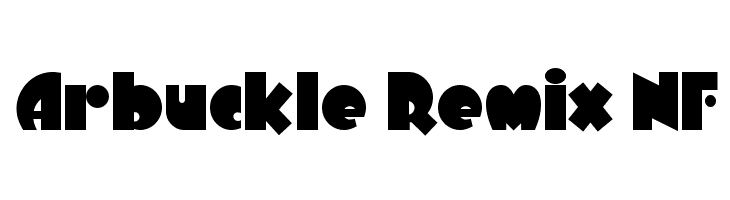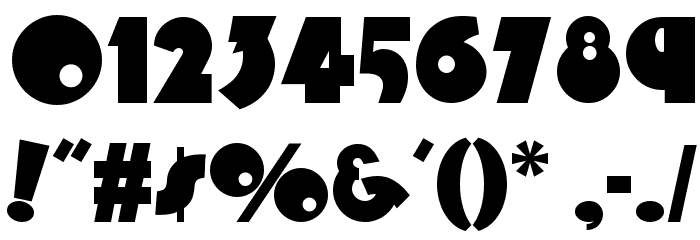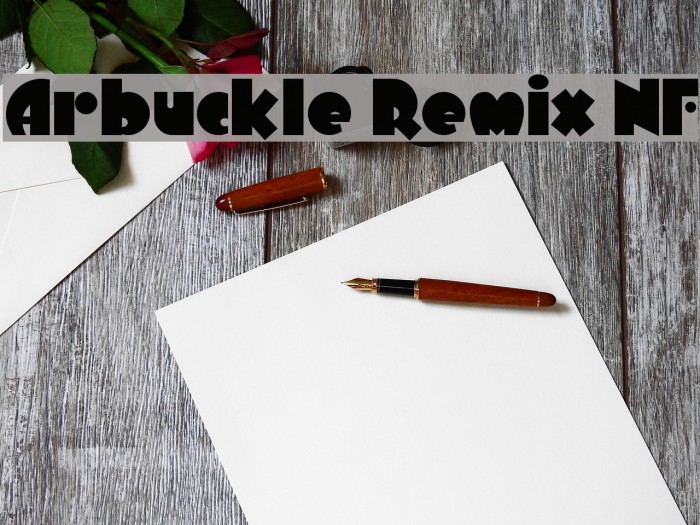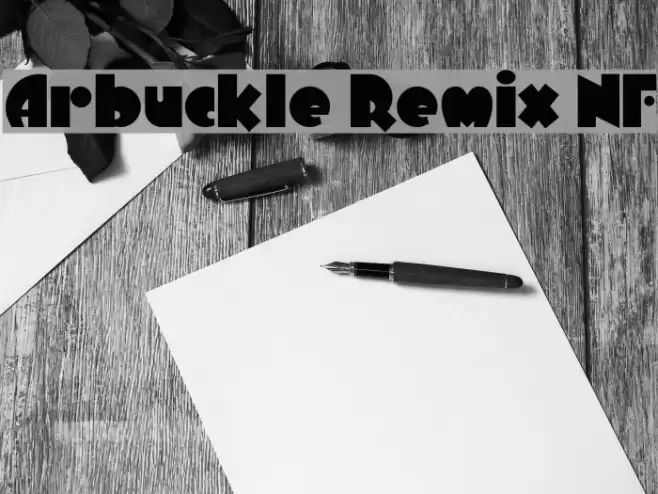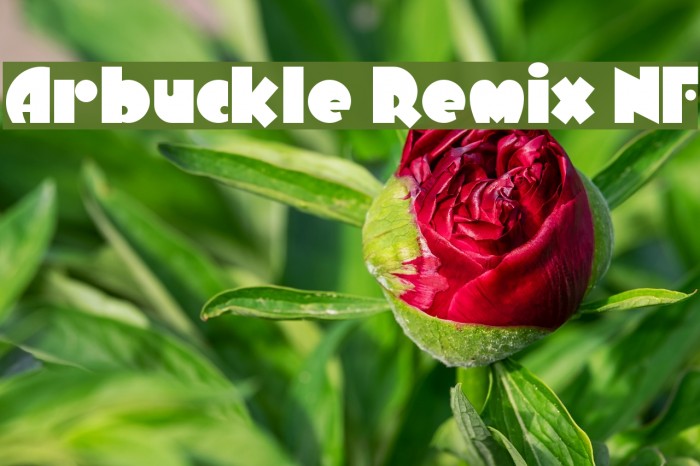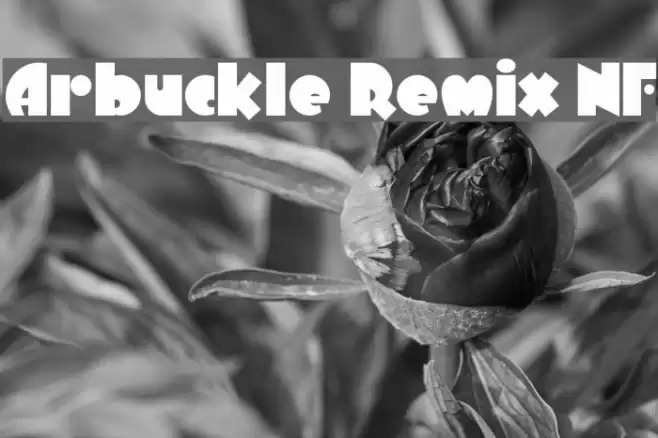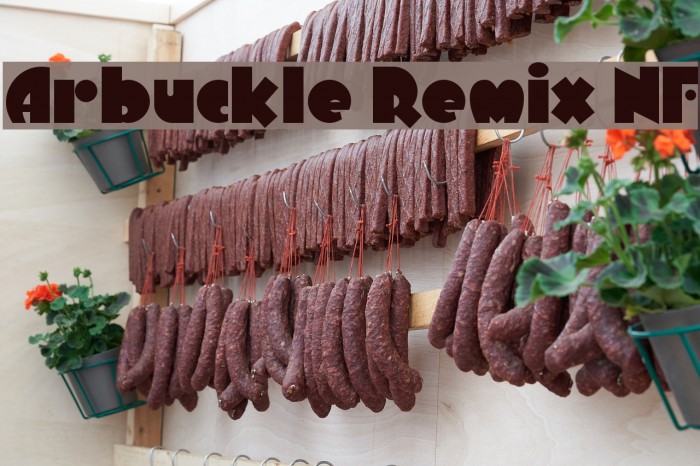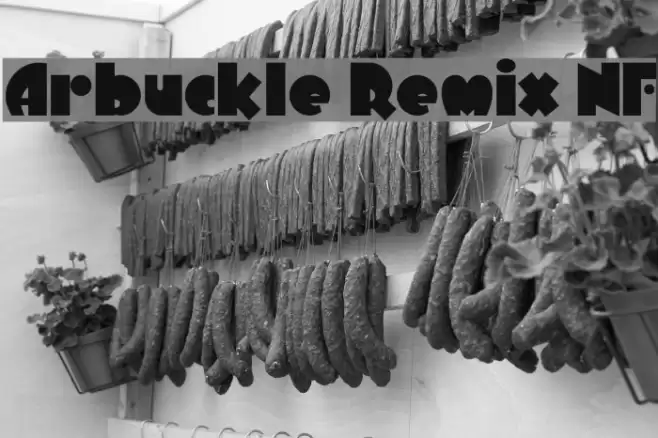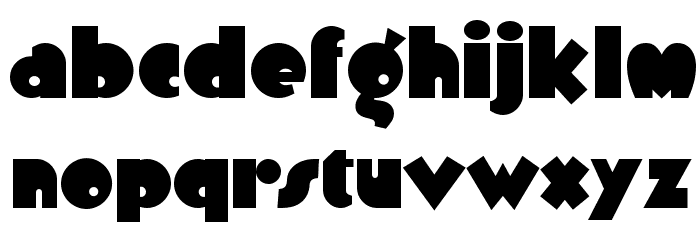
Arbuckle Remix NF Font
| Style général | Vintage, Modern |
| Projets proposés | Ideal for branding, poster design, album covers, and any project needing a bold, vintage-modern aesthetic. |